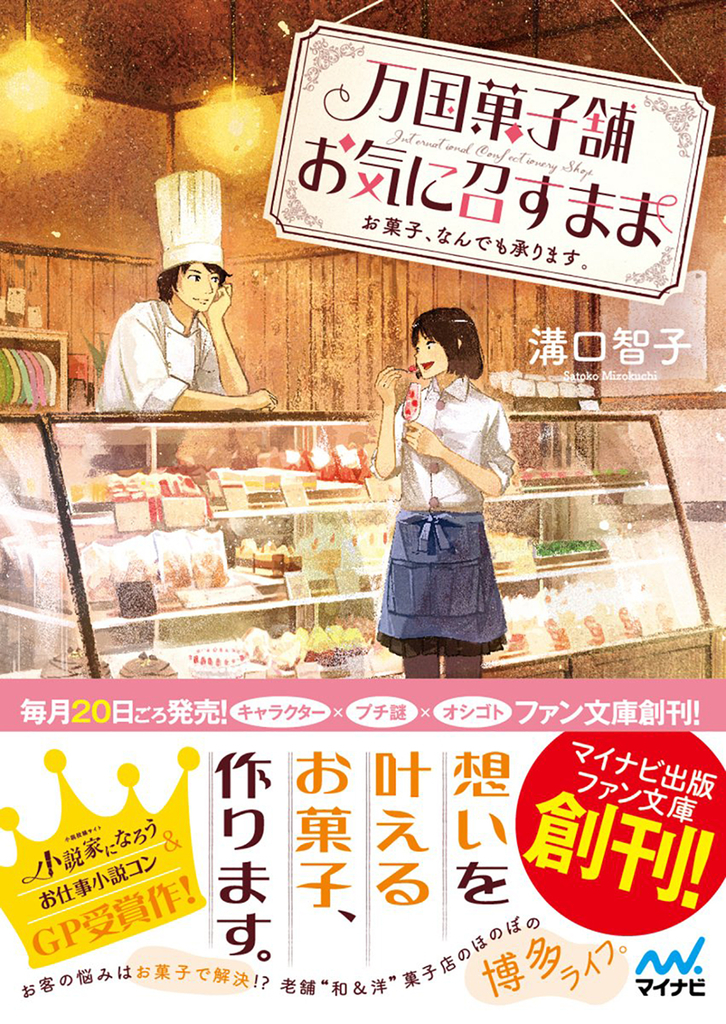
万国菓子舗 お気に召すまま
小説投稿サイト「小説家になろう」での『お仕事小説コン』にてグランプリを受賞した九州・博多の老舗菓子屋を舞台とした、著書・溝口智子、イラスト・げみ、マイナビ出版ファン文庫によるほのぼのお菓子小説シリーズ。
「万国菓子舗 お気に召すまま」シリーズのタイトルフォントはダイナフォントロマン雪を使用
「万国菓子舗 お気に召すまま」シリーズのタイトルにダイナフォントのロマン風書体「ロマン雪」が長体およびフォントを加工して使用されている。
ロマン雪
1925年の藤原太一著書による『図案化せる実用文字』から着想を得て、図中の婦人の華麗な装いや愛らしいスタイルをヒントにして、大正末期から昭和初期にかけての古典ロマンの雰囲気を再現した書体。ひし形など独特の字形が大きなインパクトを与える事から、ロゴやPOPなどで大きく活用できる。